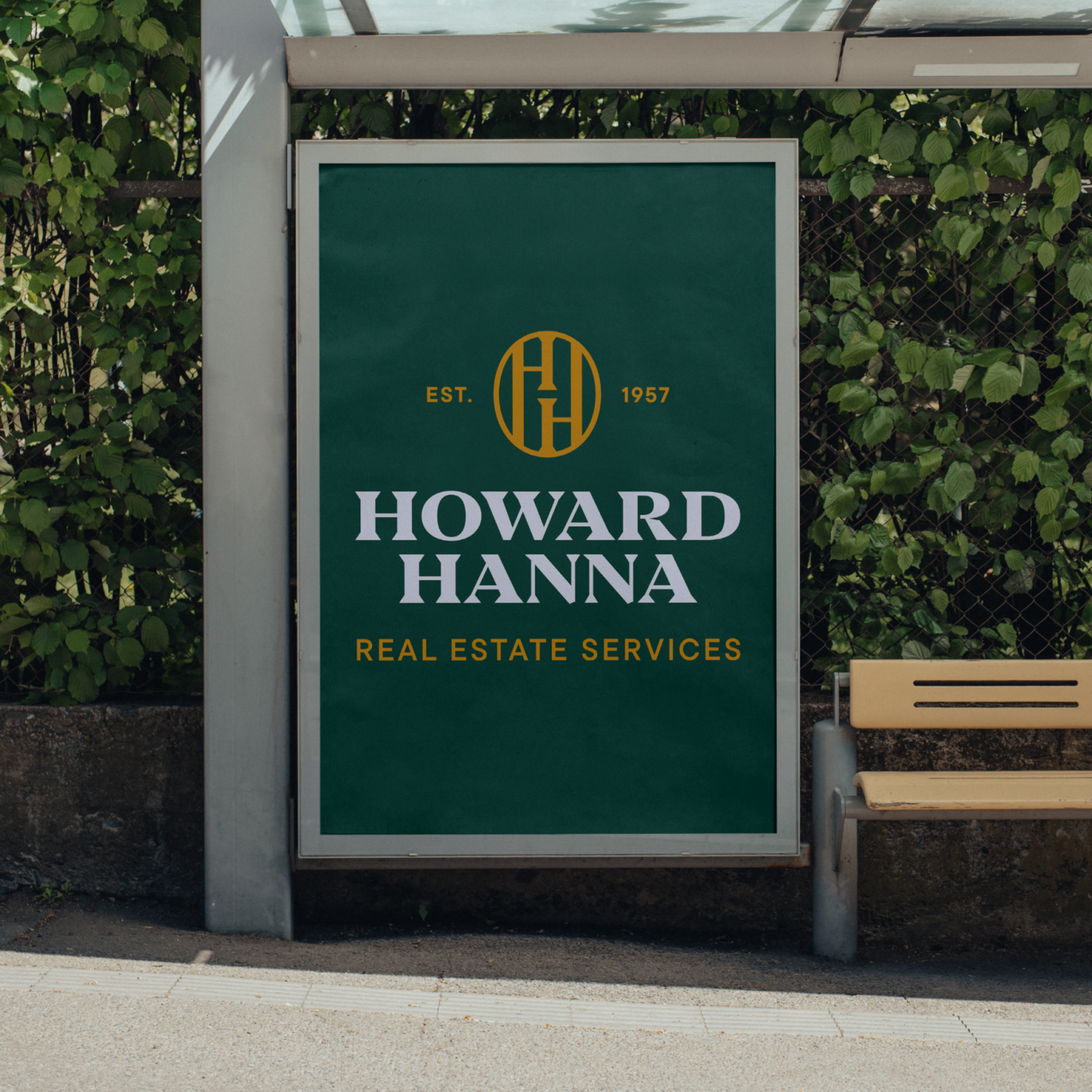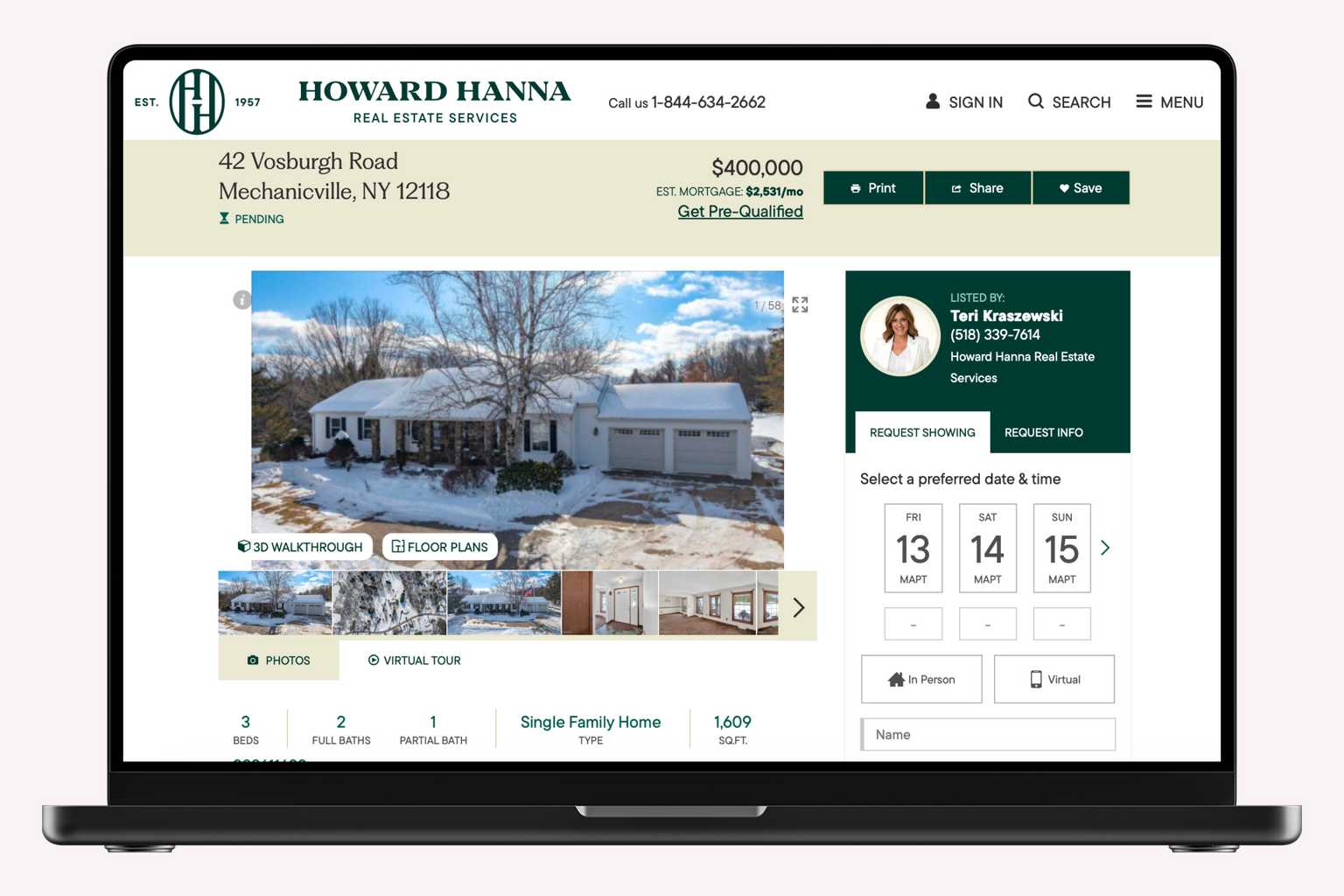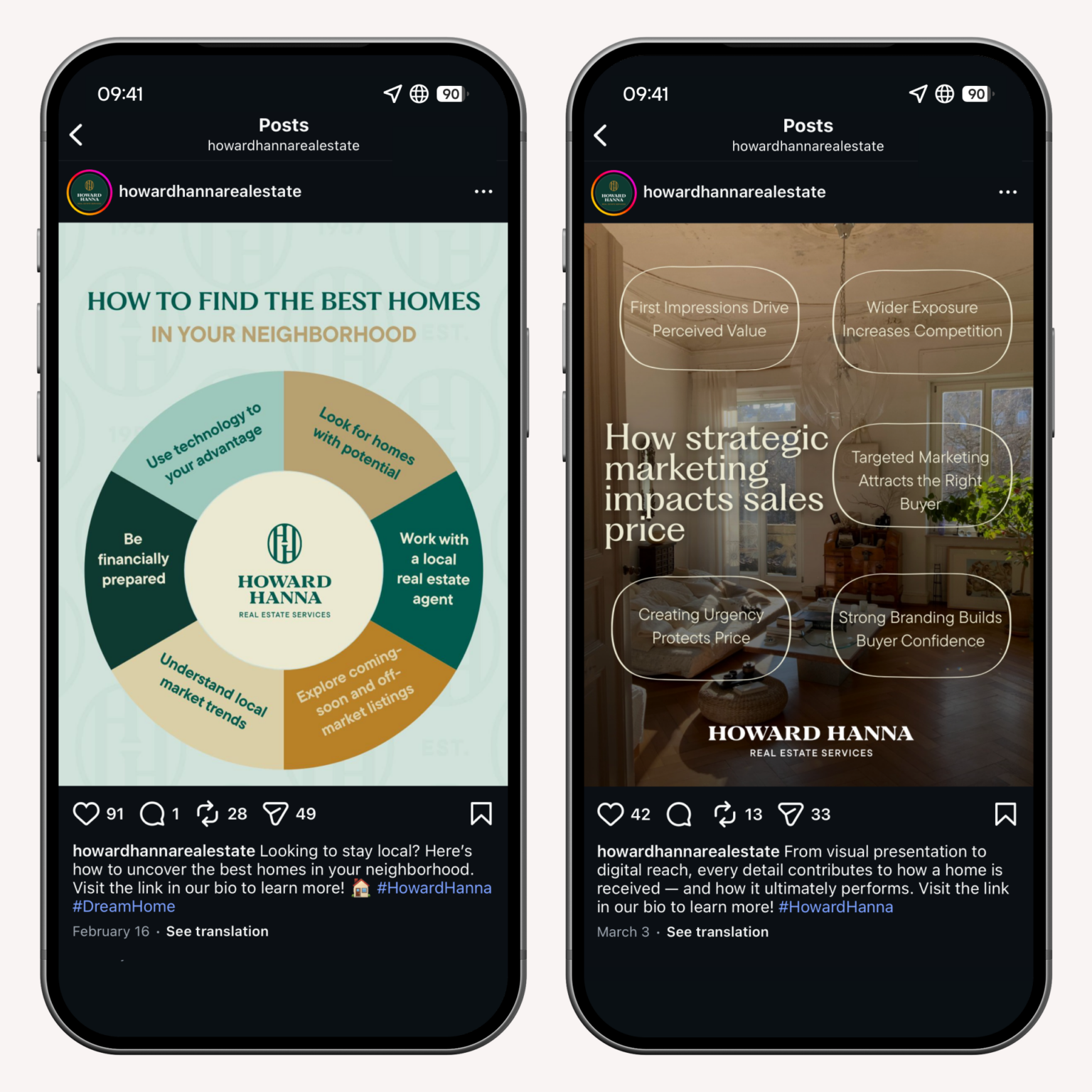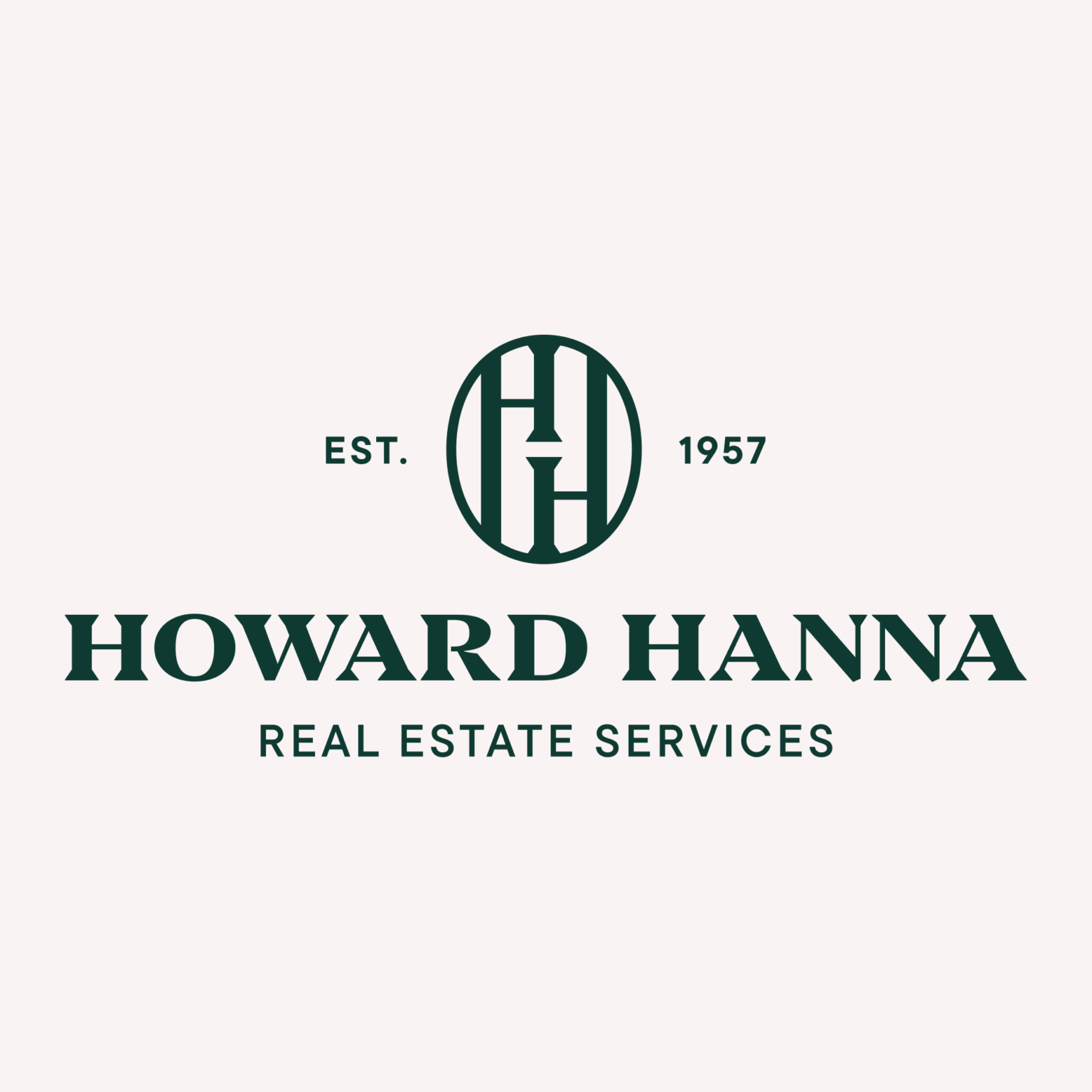
Универсальный ТТ Коммонс Про (TT Commons™ Pro) — часть фирменного стиля Howard Hanna, крупнейшей частной брокерской компании по недвижимости в США.
Howard Hanna Real Estate Services предлагает полный спектр услуг по недвижимости, включая продажу, ипотечные и страховые услуги. Основанная супружеской парой в 1957 году, компания остаётся семейным бизнесом. ТТ Коммонс Про подчёркивает миссию компании, которая строится на важности семейных ценностей, профессионального подхода и уважительного отношения как к клиентам, так и к сотрудникам.